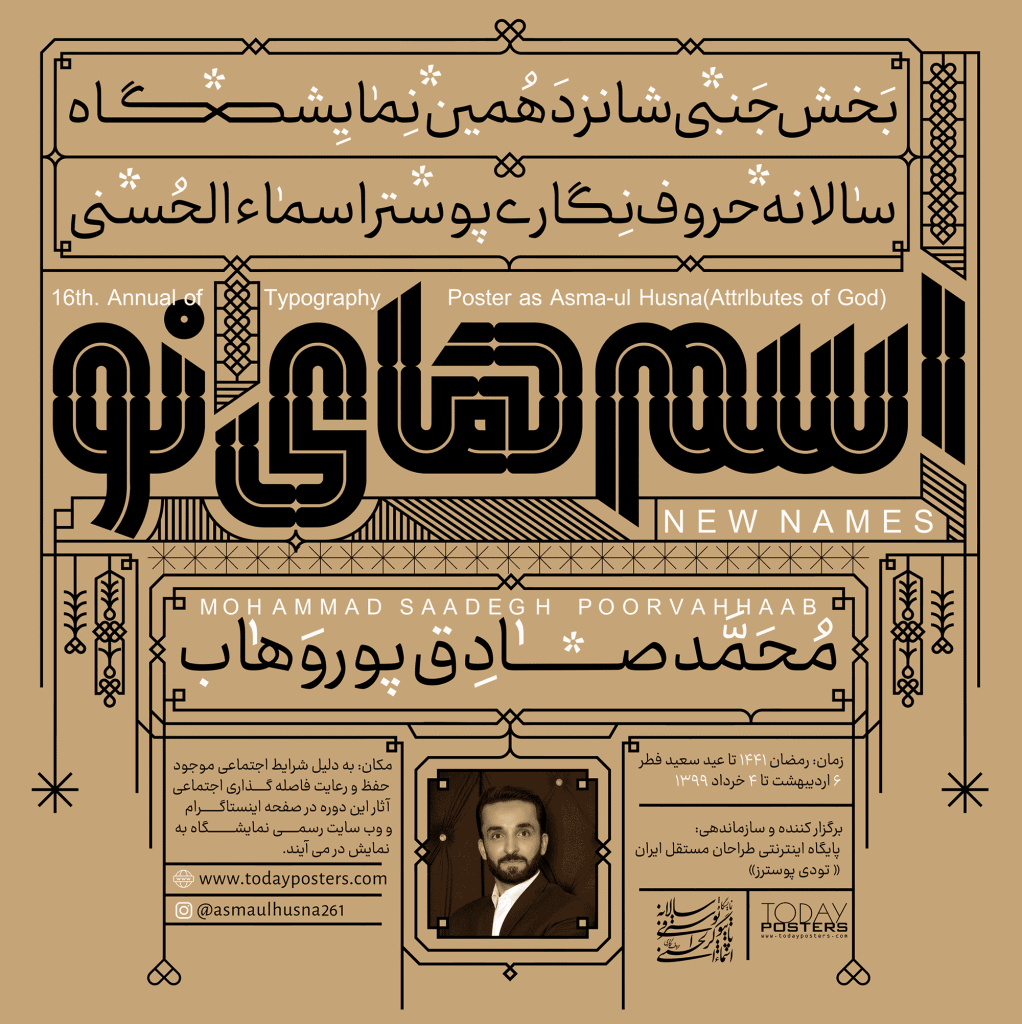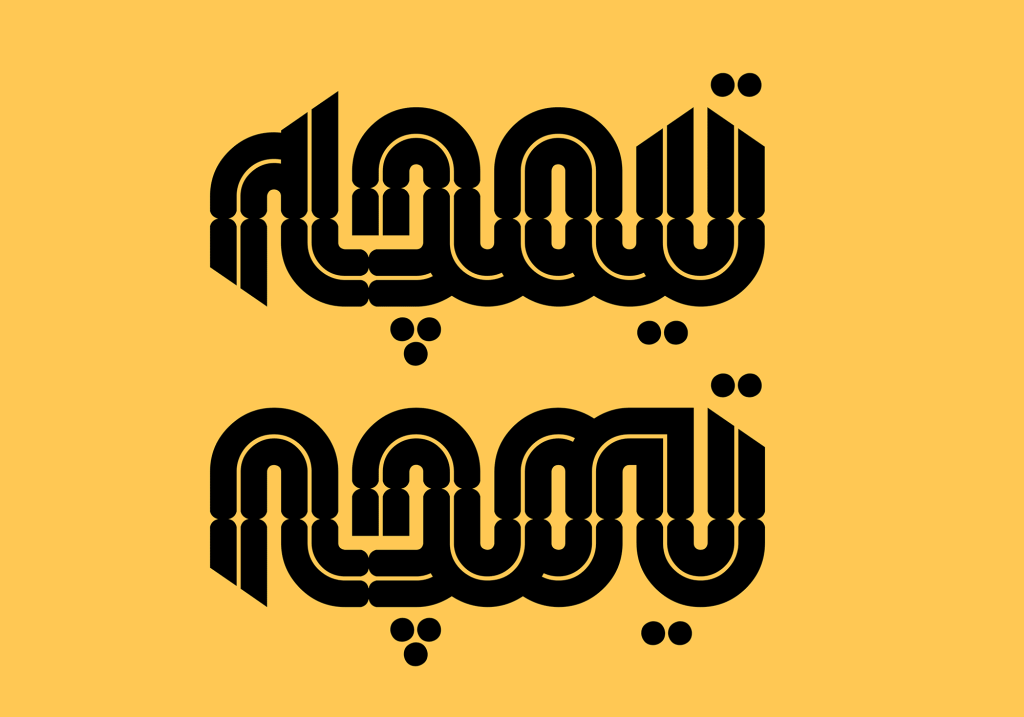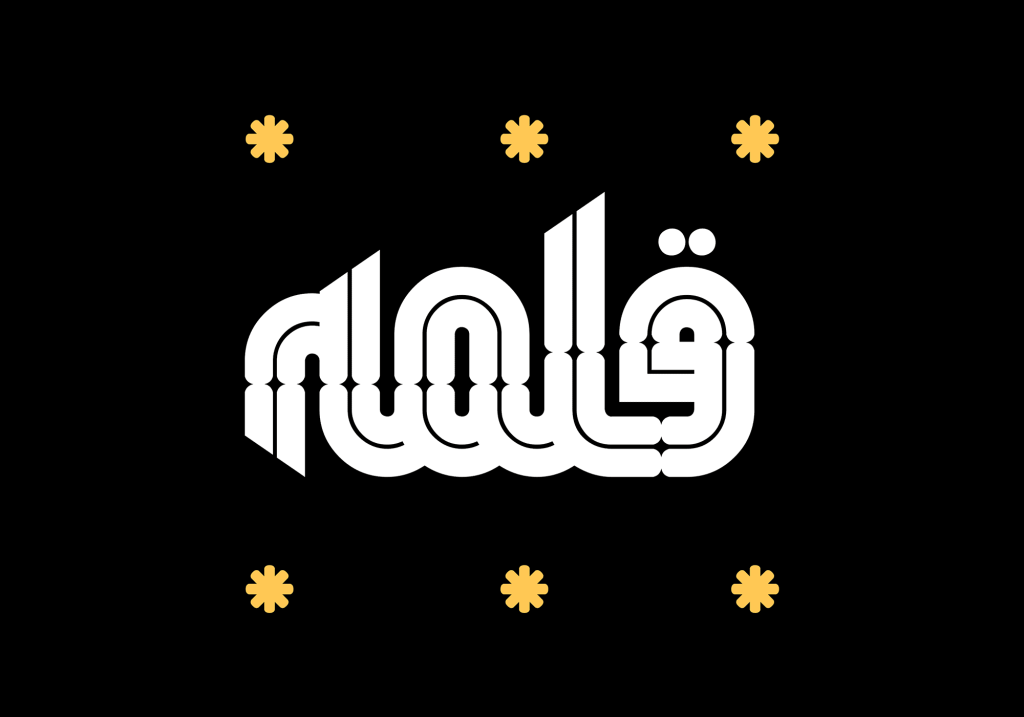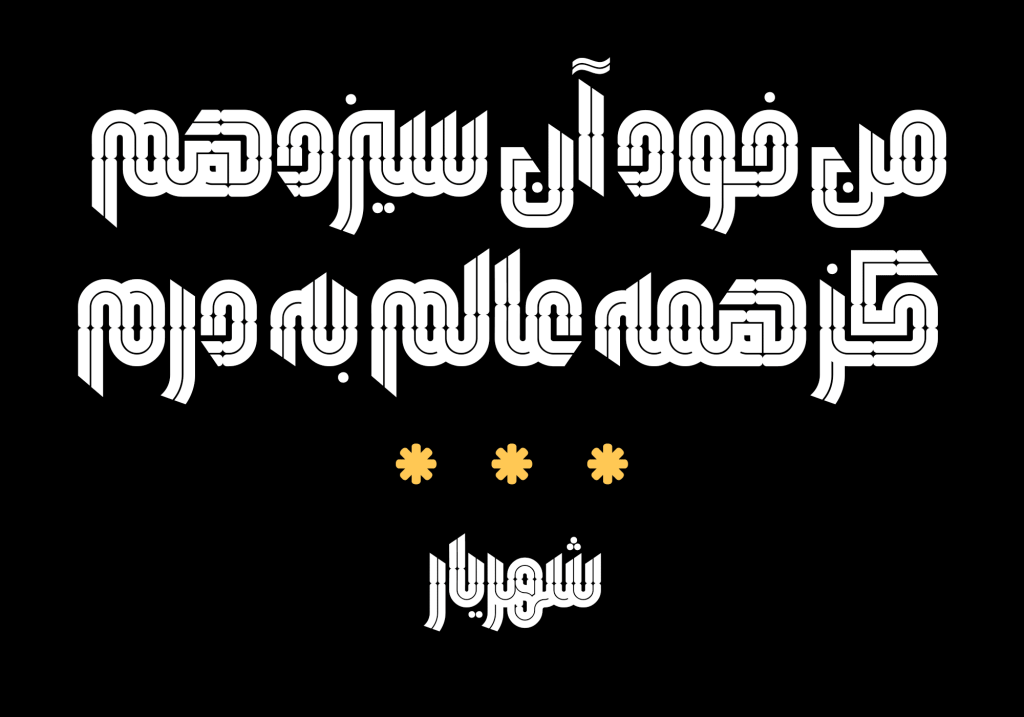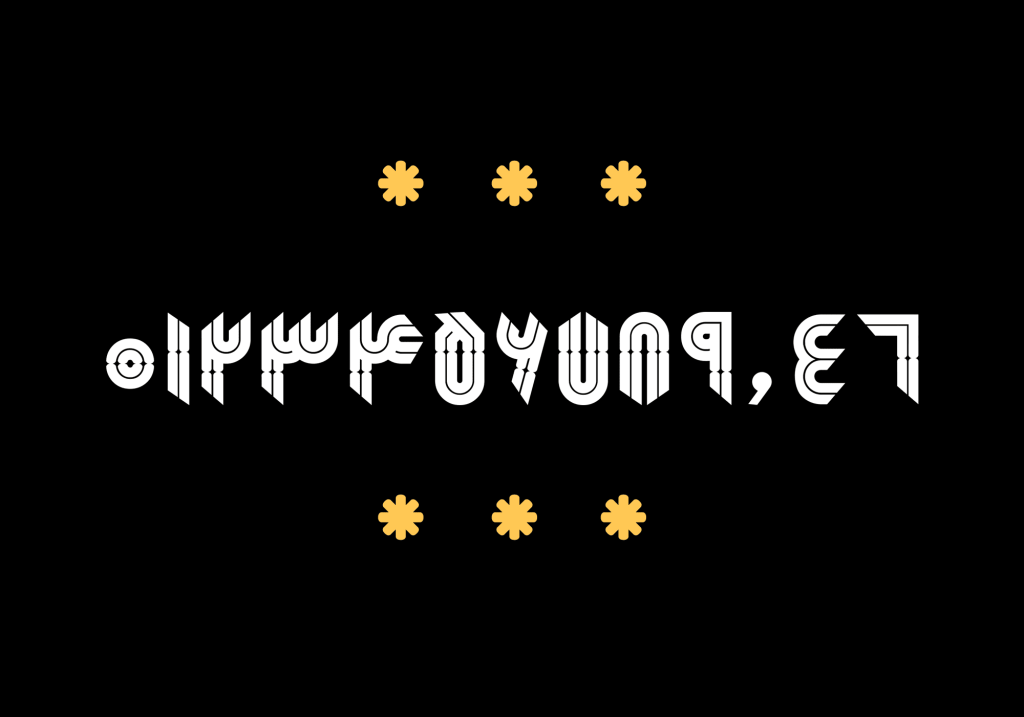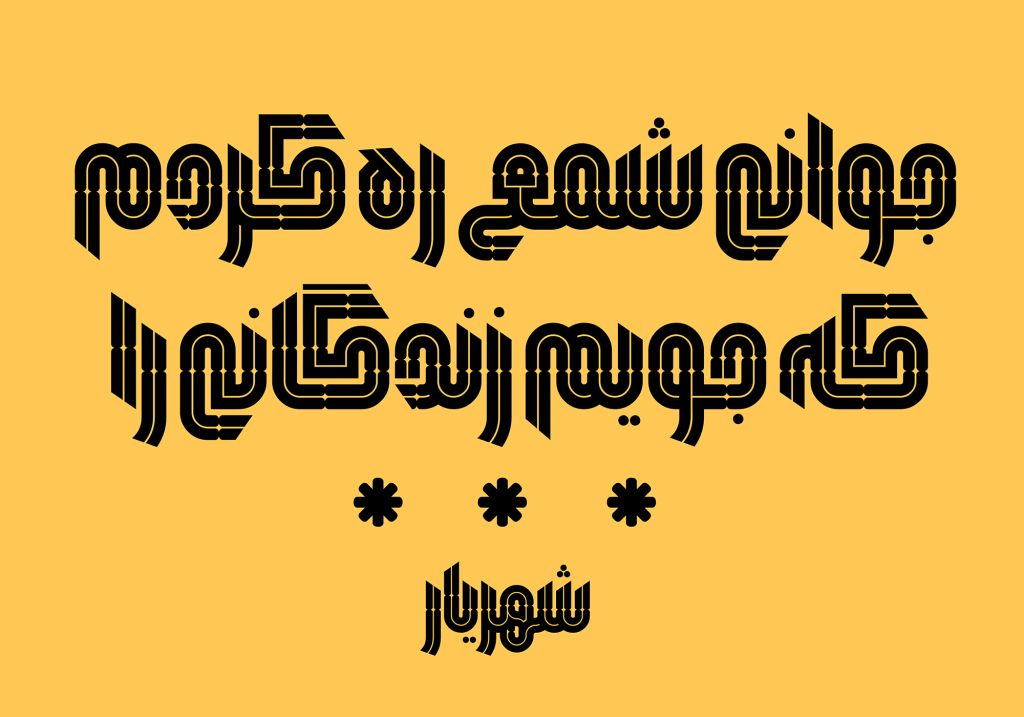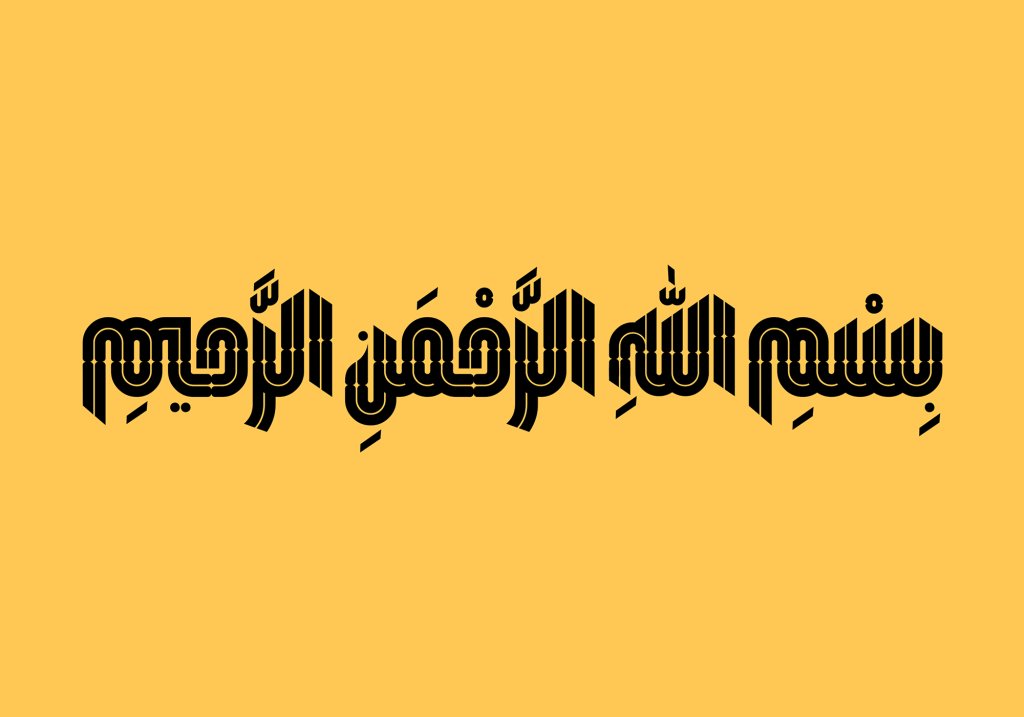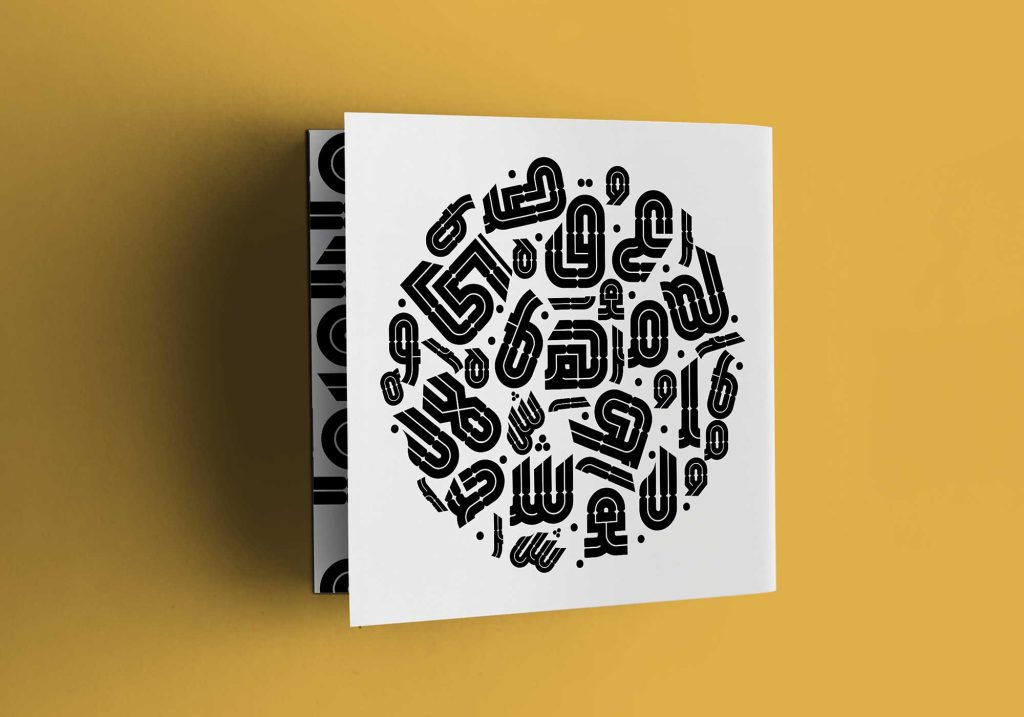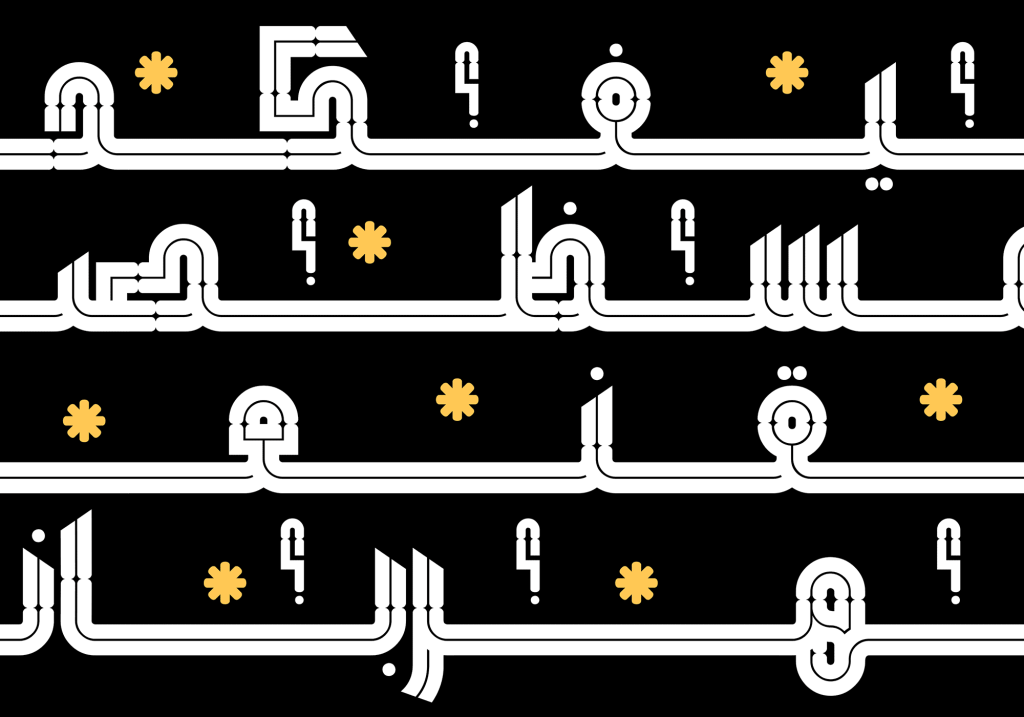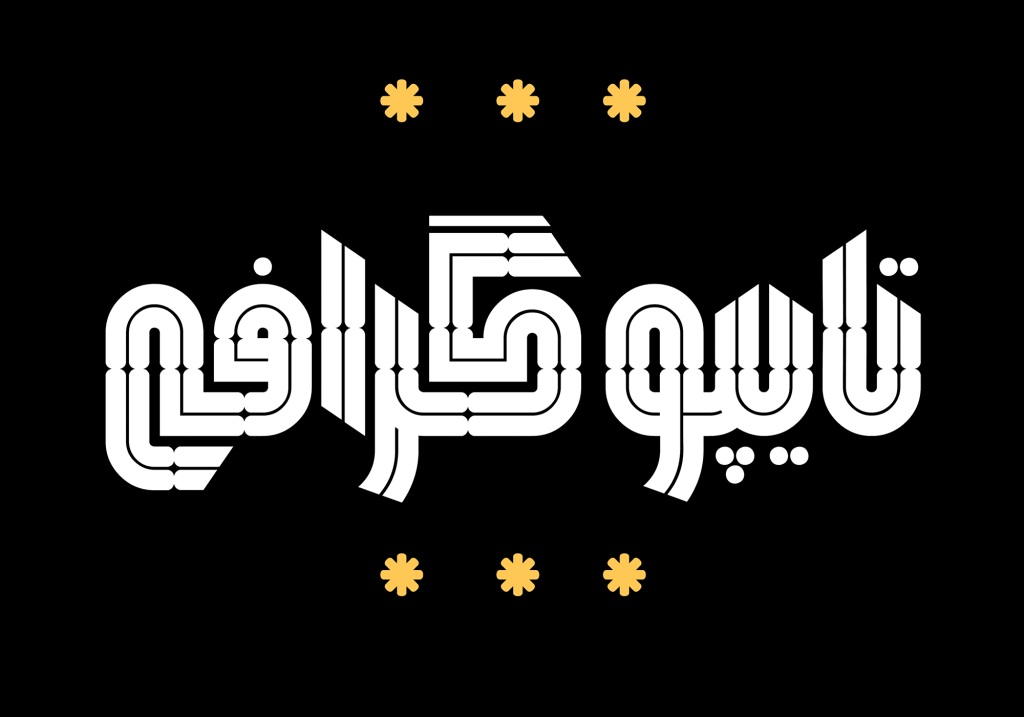
تایپ فیس همتا قلمی تزئینی به سبک درون خط است که با اقتباس از کوفی تزئینی طراحی شده است. طراح فونت همتا به خوبی فرم را شناخته و از ترکیب میراث خط کوفی با هندسه شکل‌های جدیدی از حروف فارسی را خلق کند که نظیر و مانندی ندارند.
فونت همتا
همتا برای راحت و آسوده خوانی طراحی نگردیده. این تایپ فیس برای دیده شدن و خو دنمایی و بردن لذت از زیبایی فرم حروف خلق گردیده است. چنین قلمی بی نیازی اثر گرافیکی از عناصر تصویری را تضمین می نماید. حروف و گلیف ها به میزان زیادی جلوه‌گر و رخ نما بوده و حتی ممکن است این تایپ فیس بمانند خط کوفی برای پر کردن فضا استفاده شود.
طراح این قلم آقای وحید یعقوب‌لو پیش از طراحی این تایپ فیس نیز فونت یکتا را
طراحی کرده است و بدین سان شاید بتوان او را متخصص طراحی این دسته
تایپ دانست. تایپ فیس‌هایی نمایشی، هندسی و دارای حال و هوای. سنتی و
تزئینی